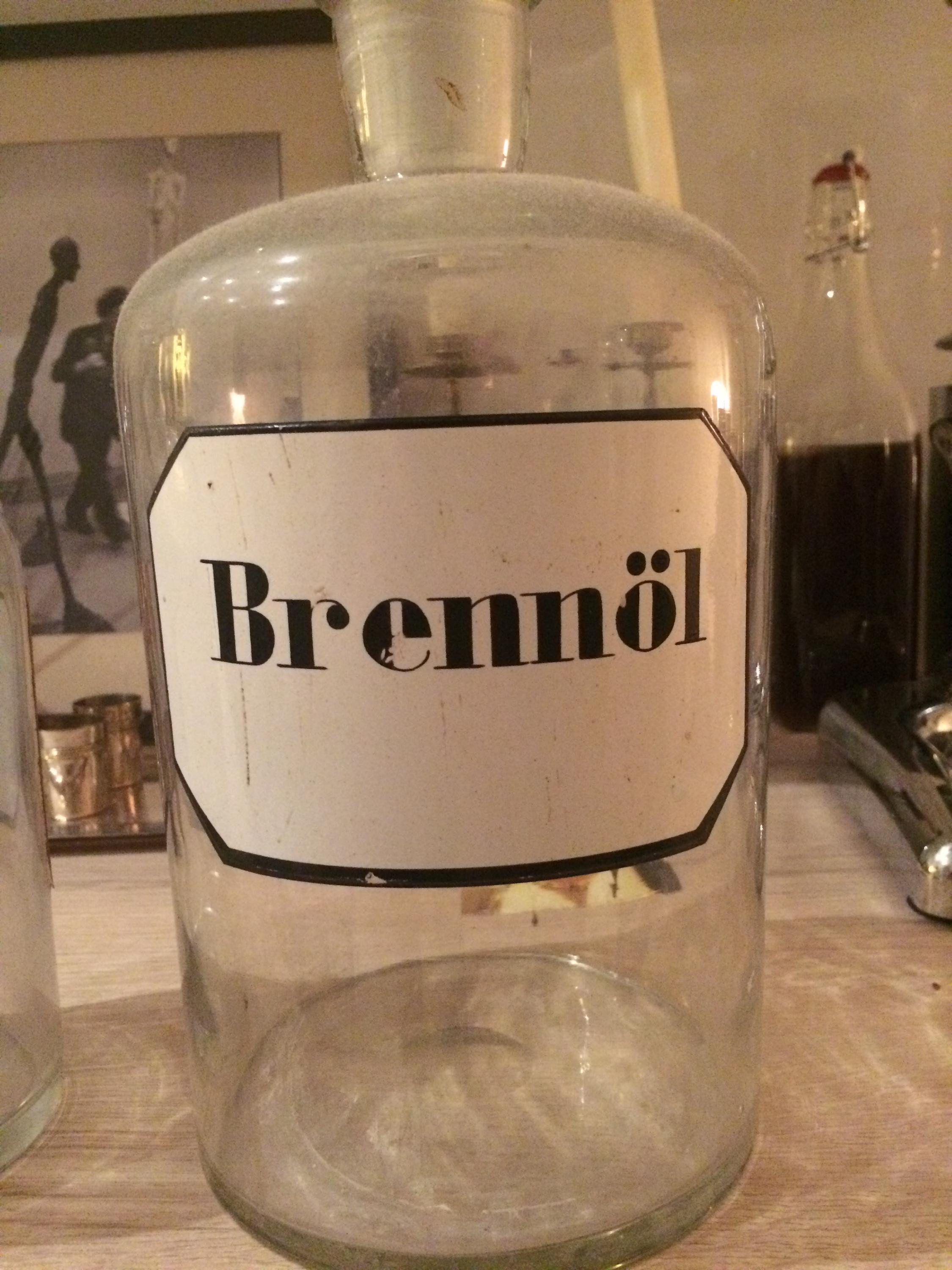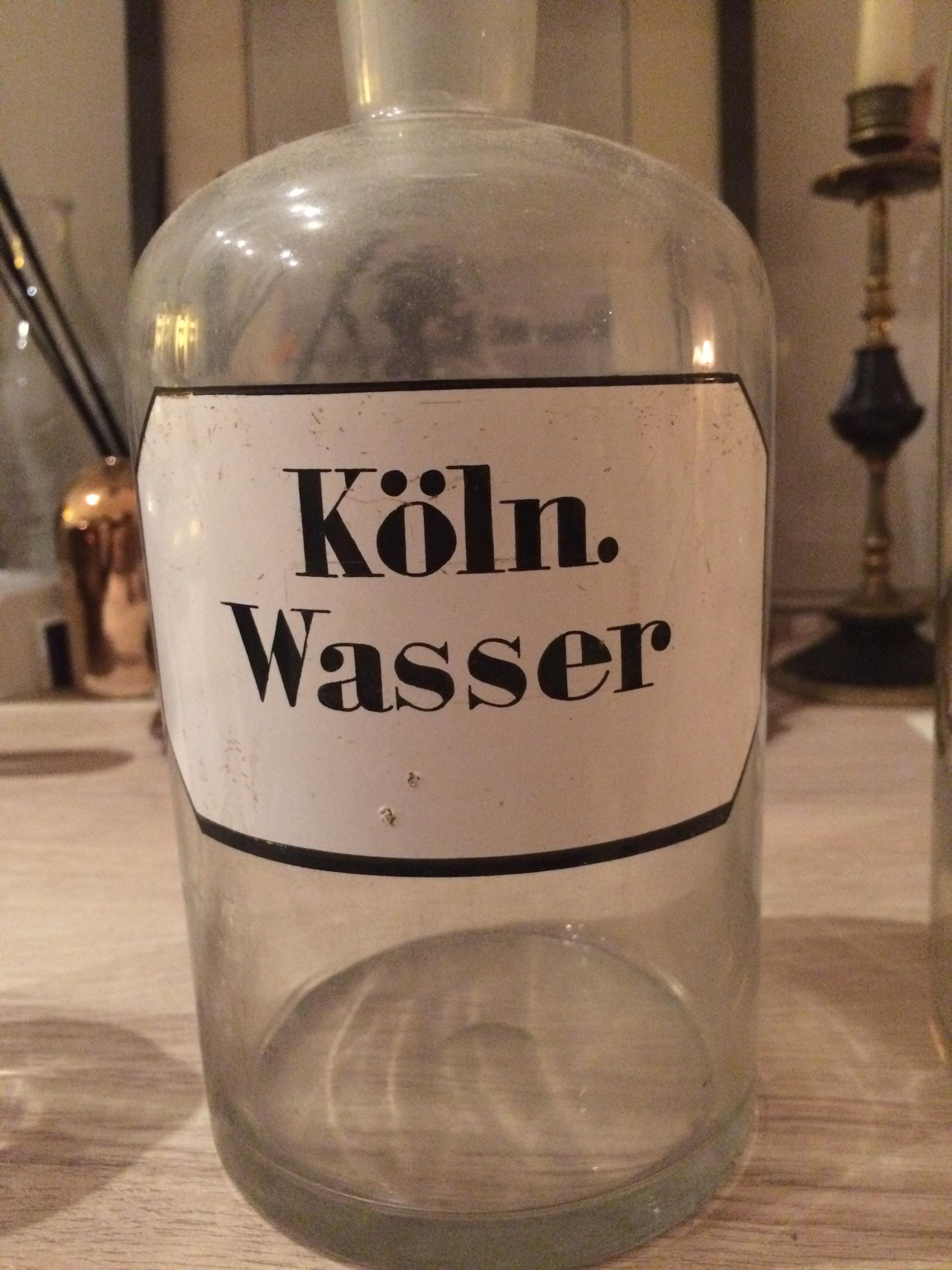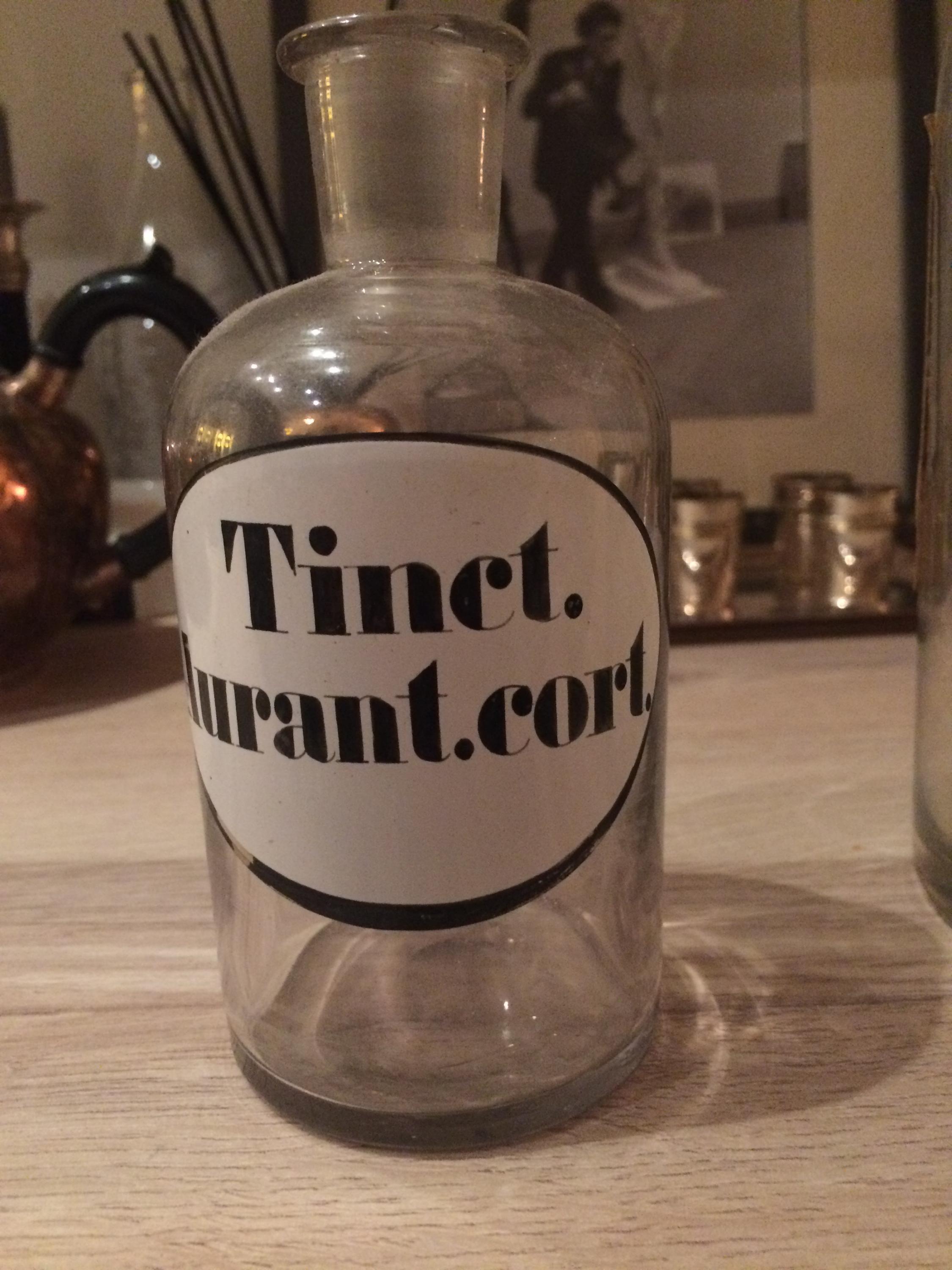
Alte Apothekerflaschen Schrift? (mit Foto)
ich bin auf der verzweifelten Suche nach dem Namen der Schriftart von alten Apothekerflaschen Etiketten.
Anbei sind ein paar Fotos mit der Schriftart die ich suche.
Wenn ihr Ideen habt wie ich diese herausfinden kann oder ihr direkt wisst welche es ist würde ich mich sehr über eure Ratschläge freuen.
Diese Beschriftungen stammen aus einer Zeit, in der nahezu alles schriftliche, das nicht im Buchdruck auf Papier gedruckt wurde frei von Hand geschrieben, bzw gezeichnet wurde. Betrachtet man gleiche Buchstaben genauer, sieht man deutlich die Unterschiede durch die Handarbeit.
Auch wurden zumeist diese Schriften mit Aufkommen digitaler Schriften nicht digitalisiert, da es oft schwierig ist, komplette Alphabete zu finden, und man dann buchstäblich diese Schrift frei gestalten muss.
Das mit der Handarbeit hilft mir schon sehr.
Habt ihr jedoch eine Idee welche Schrift so ähnlich aussehen könnte?
Aber diese komischen, kantigen Verbindungen von den Serifen zum Haarstrich wie beim W oder K wird man so wohl kaum finden (hoffentlich:shock:).
Auch nicht so weit weg und mit K und W speziell für Schnitzel:
Klar doch – die erwähnten Serifen finde ich nicht :baeh: